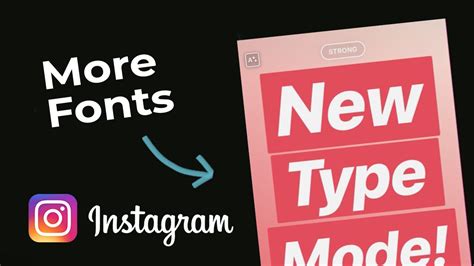
Fonte Instagram 2020: Uma Introdução
Com o aumento das pessoas recebendo seus conteúdos em primeira mão no Instagram, aumentou também a necessidade de usar fontes atraentes e originais para conteúdos visuais. Esta necessidade criou o uso de fontes personalizadas para o Instagram, que são fontes especialmente projetadas para serem usadas nas plataformas de mídia social. Estas fontes são conhecidas como fontes Instagram 2020.
As fontes Instagram 2020 são fontes que se destinam a usuários do Instagram e foram projetadas para serem usadas nas postagens do Instagram. Estas fontes são projetadas para serem acessíveis, fáceis de ler e modernas. Essas fontes são projetadas para se encaixar perfeitamente no formato do Instagram e para se destacar, pois são fontes originais que não podem ser encontradas em outro lugar. Estas fontes são criadas especificamente para o Instagram, o que significa que elas são projetadas para se encaixar perfeitamente no formato do Instagram.
Por que usar as Fontes do Instagram 2020?
Ao usar fontes personalizadas para o Instagram, você poderá destacar seus conteúdos e criar uma aparência única e moderna. As fontes do Instagram 2020 são projetadas para serem acessíveis, fáceis de ler e modernas. Além disso, elas são projetadas para se encaixar perfeitamente no formato do Instagram, o que significa que elas se destacarão das fontes padrão da plataforma. Ao usar fontes personalizadas, você pode criar uma aparência única e atraente para seus conteúdos e destacar-se dos outros usuários.
Como encontrar Fontes Instagram 2020?
Encontrar fontes Instagram 2020 pode ser complicado, pois a maioria das fontes disponíveis não estão projetadas especificamente para o Instagram. Felizmente, há vários sites que oferecem fontes Instagram 2020 que foram projetadas especificamente para usuários do Instagram. Esses sites permitem que você pesquise e selecione fontes específicas para usar em seus conteúdos de acordo com o seu estilo e preferências. Ao usar fontes personalizadas, você pode destacar seus conteúdos e criar uma aparência única e moderna para os seus posts no Instagram.
Como usar Fontes Instagram 2020?
Fontes Instagram 2020: Uma das Melhores Formas de Destacar Seus Conteúdos
As fontes Instagram 2020 são projetadas para serem acessíveis, fáceis de ler e modernas. Estas fontes são projetadas para se encaixar perfeitamente no formato do Instagram e para destacar seus conteúdos da multidão. Se você estiver procurando um jeito criativo de destacar seus conteúdos no Instagram, as fontes Instagram 2020 são uma ótima opção. Além disso, como as fontes são especificamente projetadas para o Instagram, você não terá que se preocupar com elas não se encaixando no formato da plataforma.